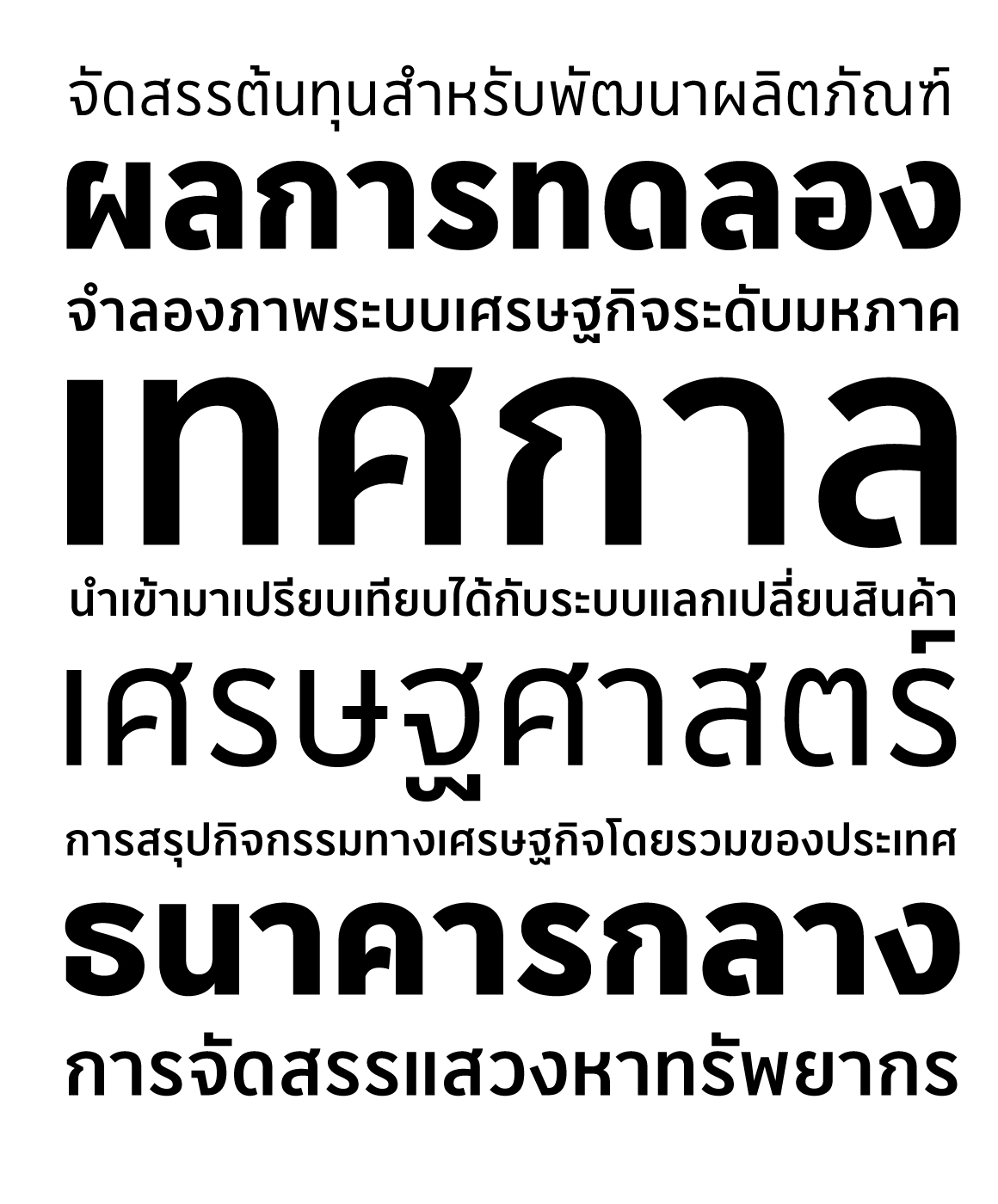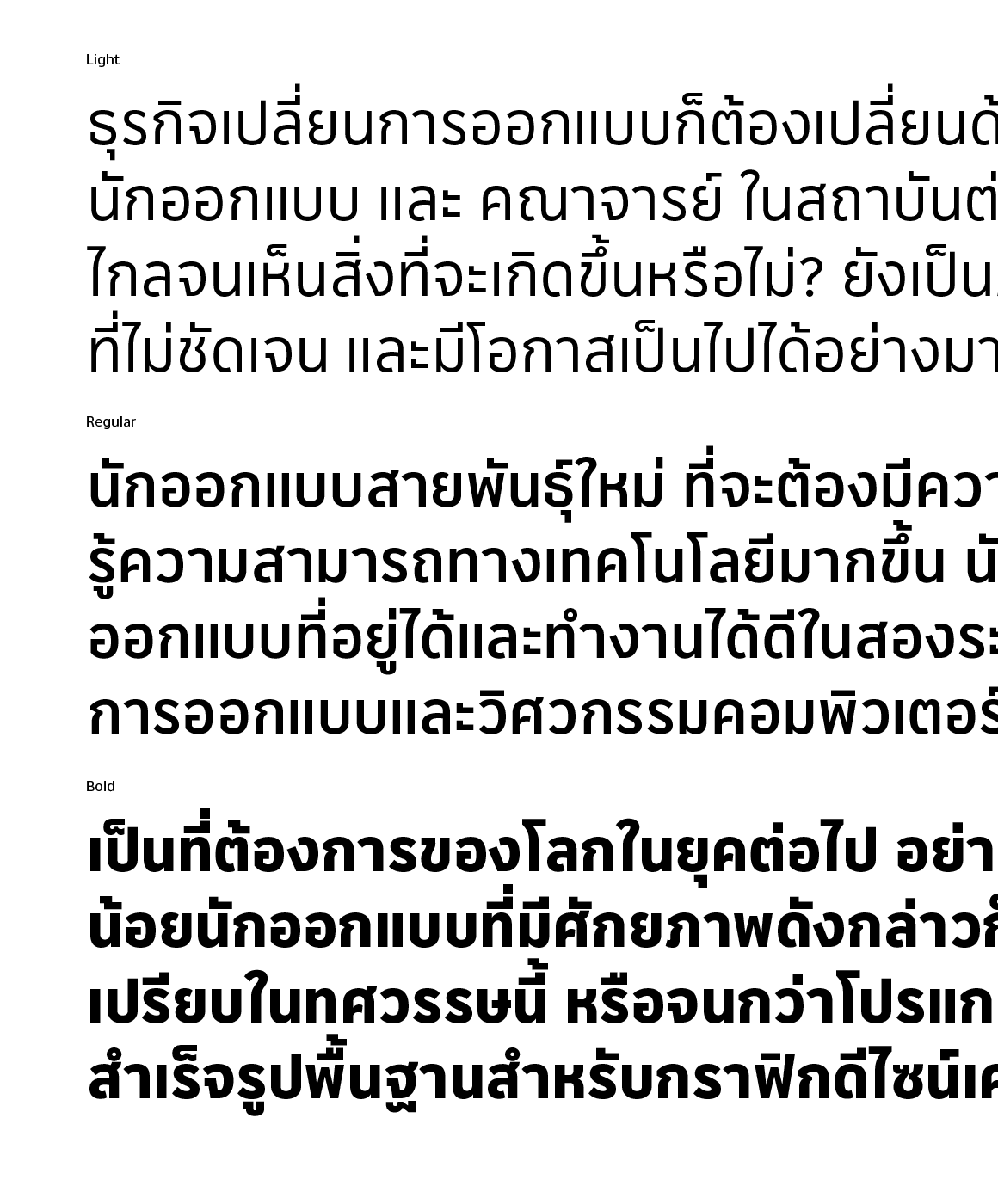
Montree
Montree™ (มนตรี) แบบตัวอักษรแบบ LoopLess Terminal ที่มีความเป็น Humanist สูง
Name : Montree
Weight : Light, Regular and Bold
Language : Latin 1 / Thai
Release Date : 2018
Designer :Thanarat Vachiruckul, Parin Rungpattarathakun
Technician : Thanarat Vachiruckul, Suppakit Chalermlarp